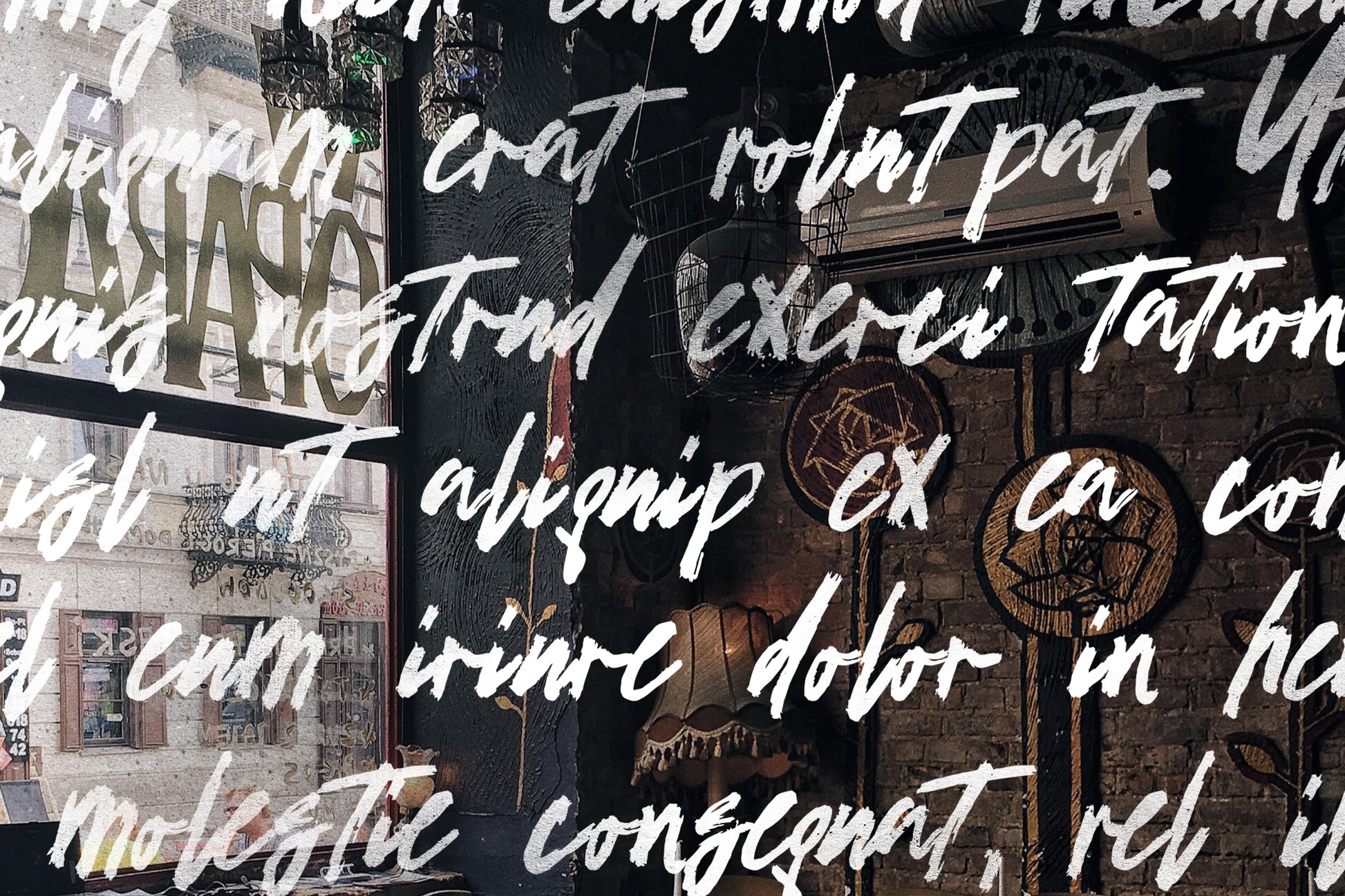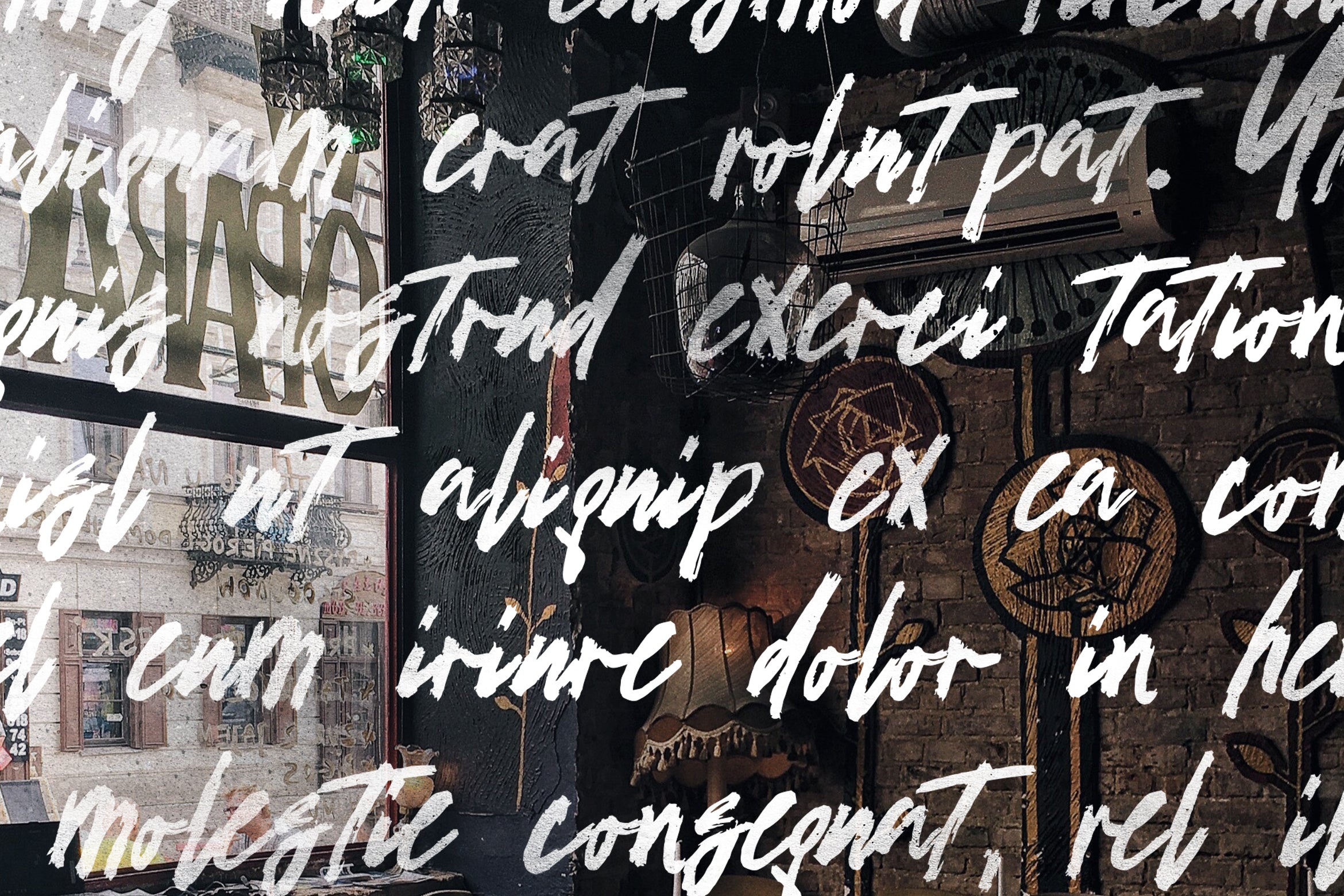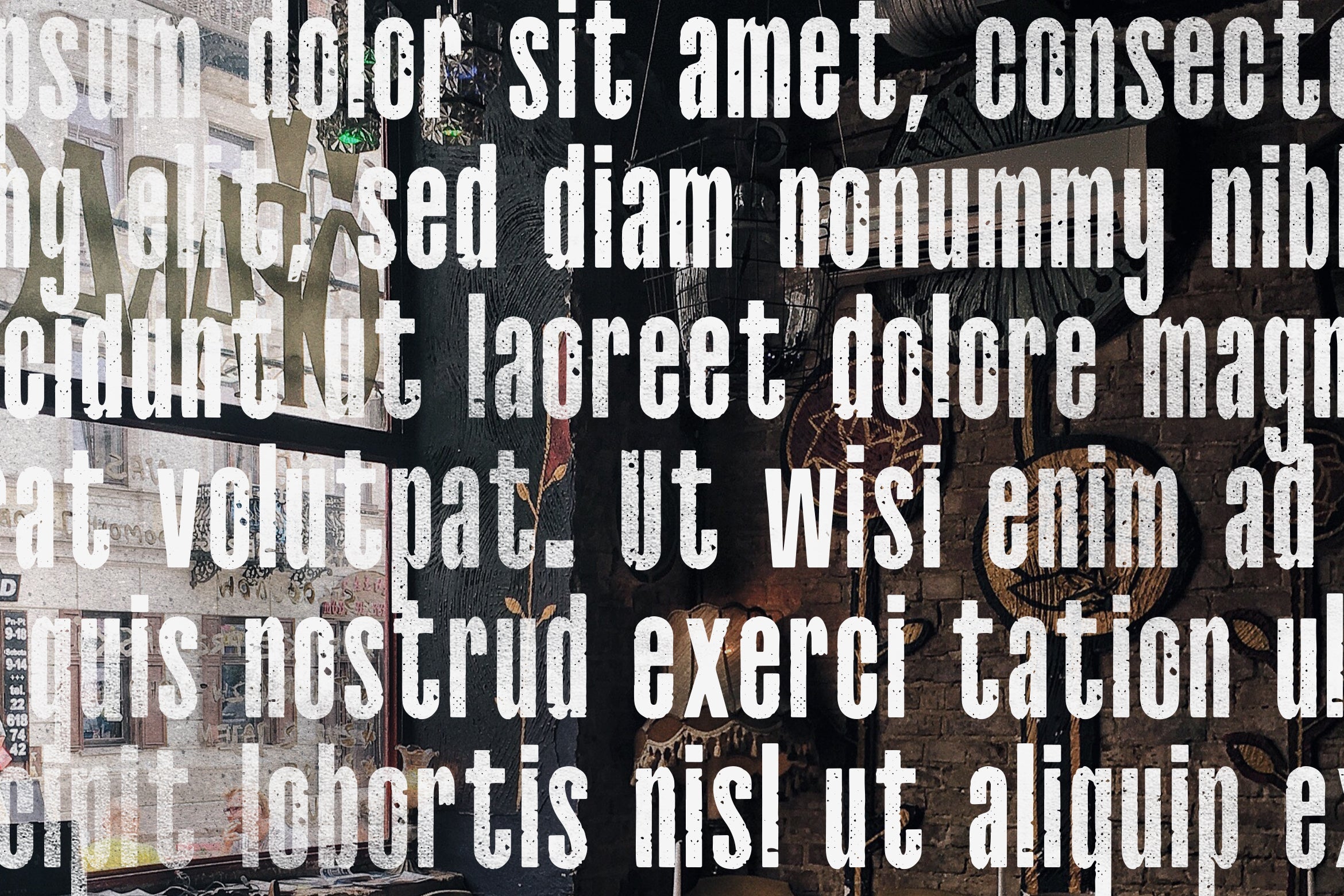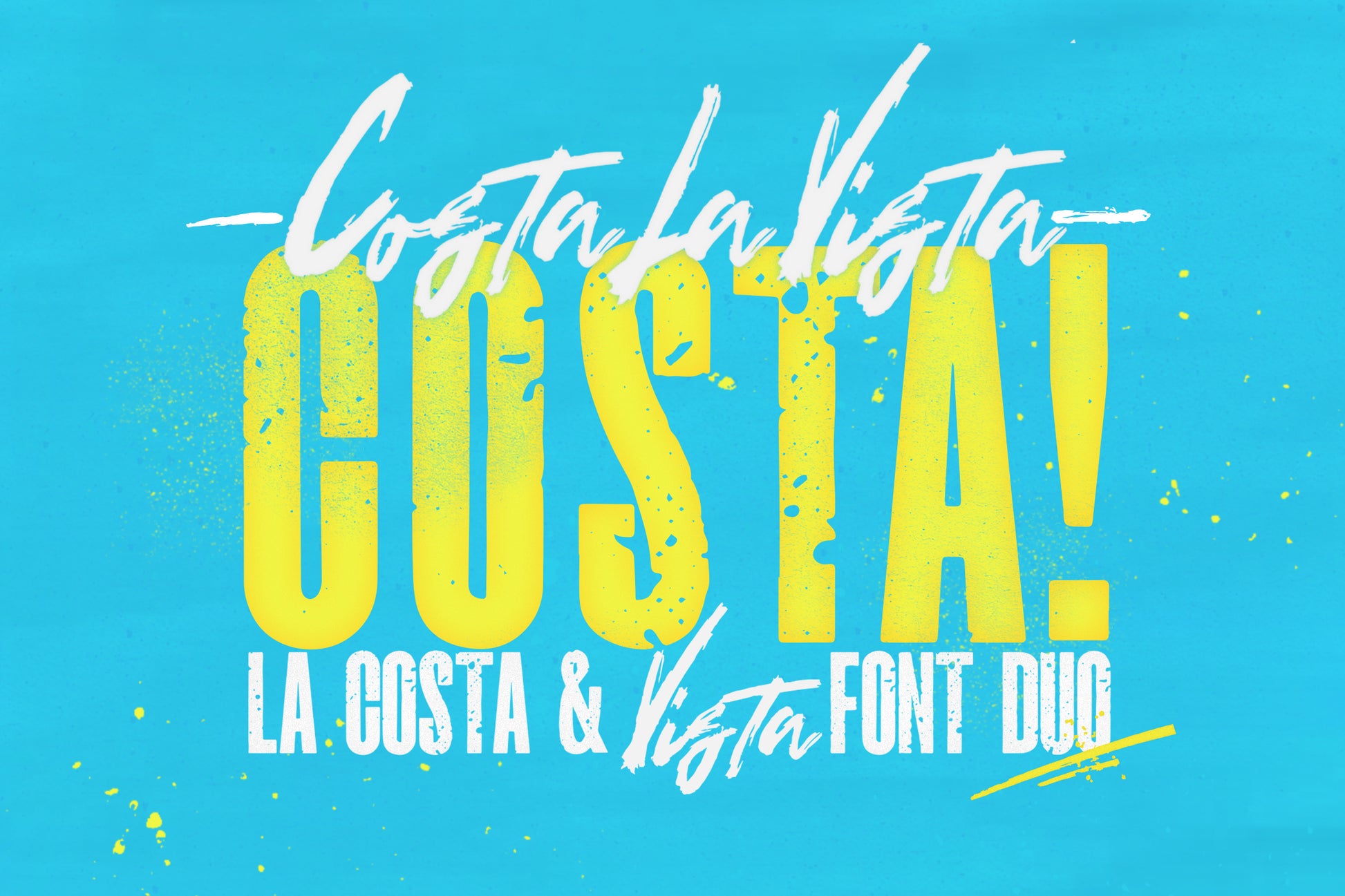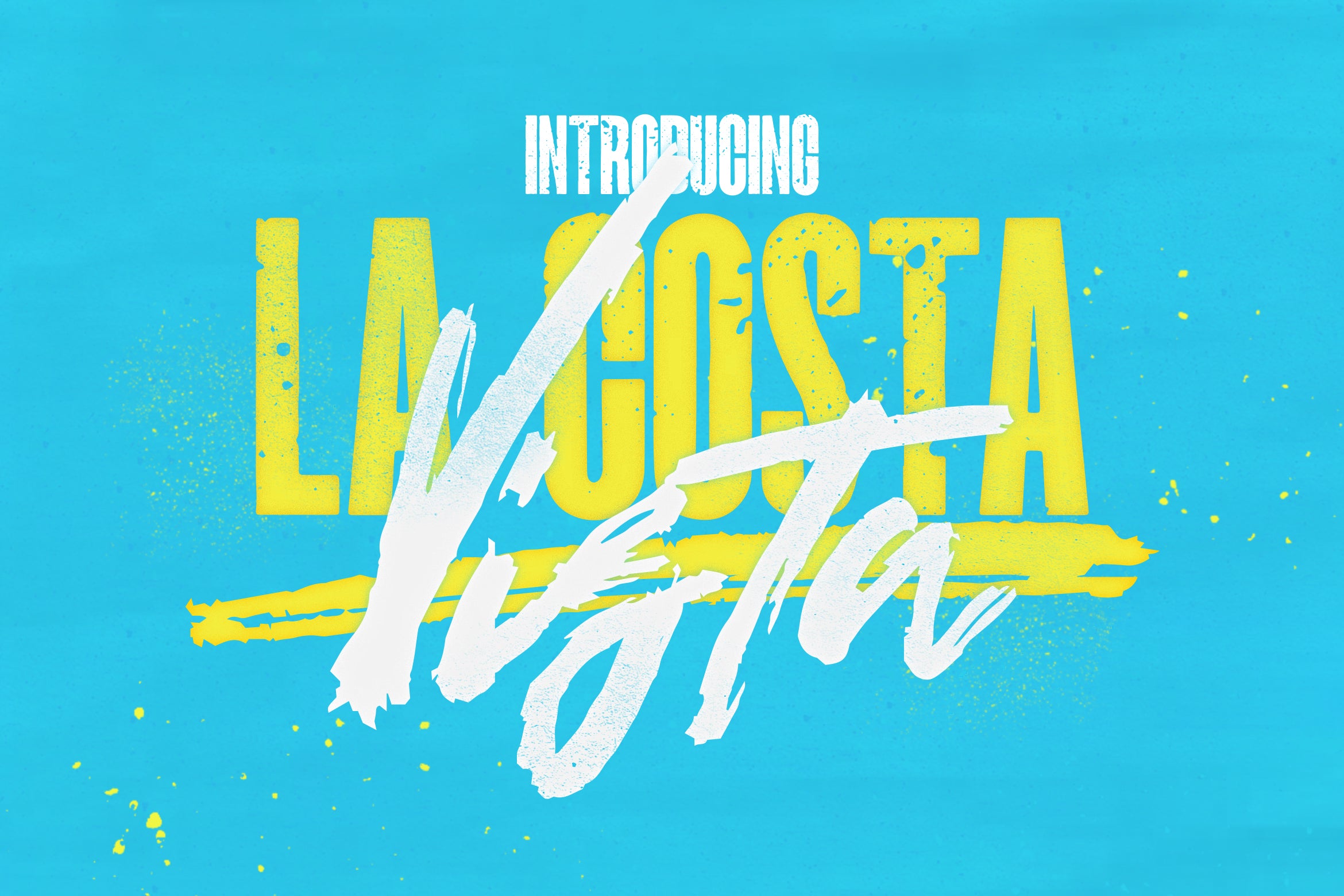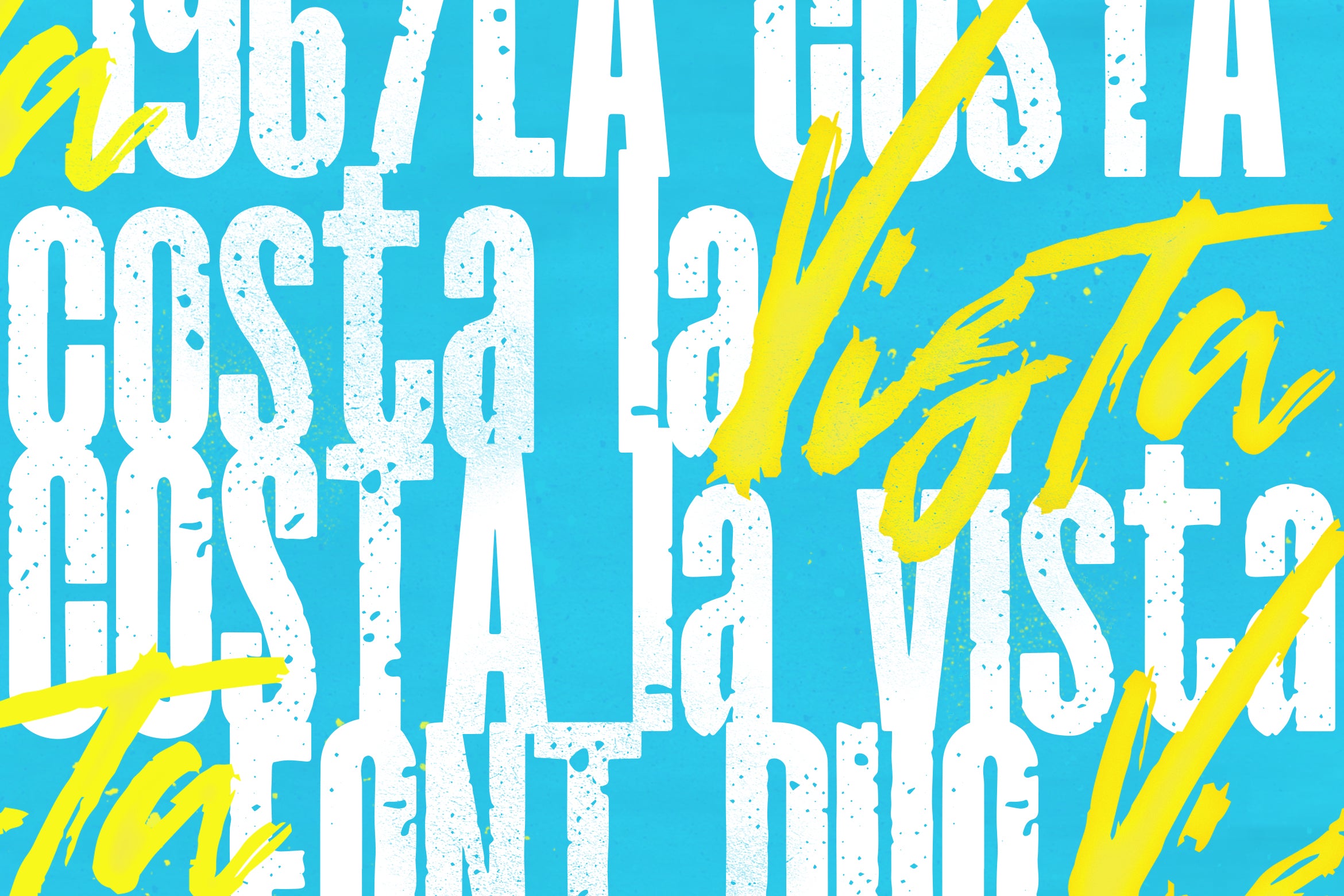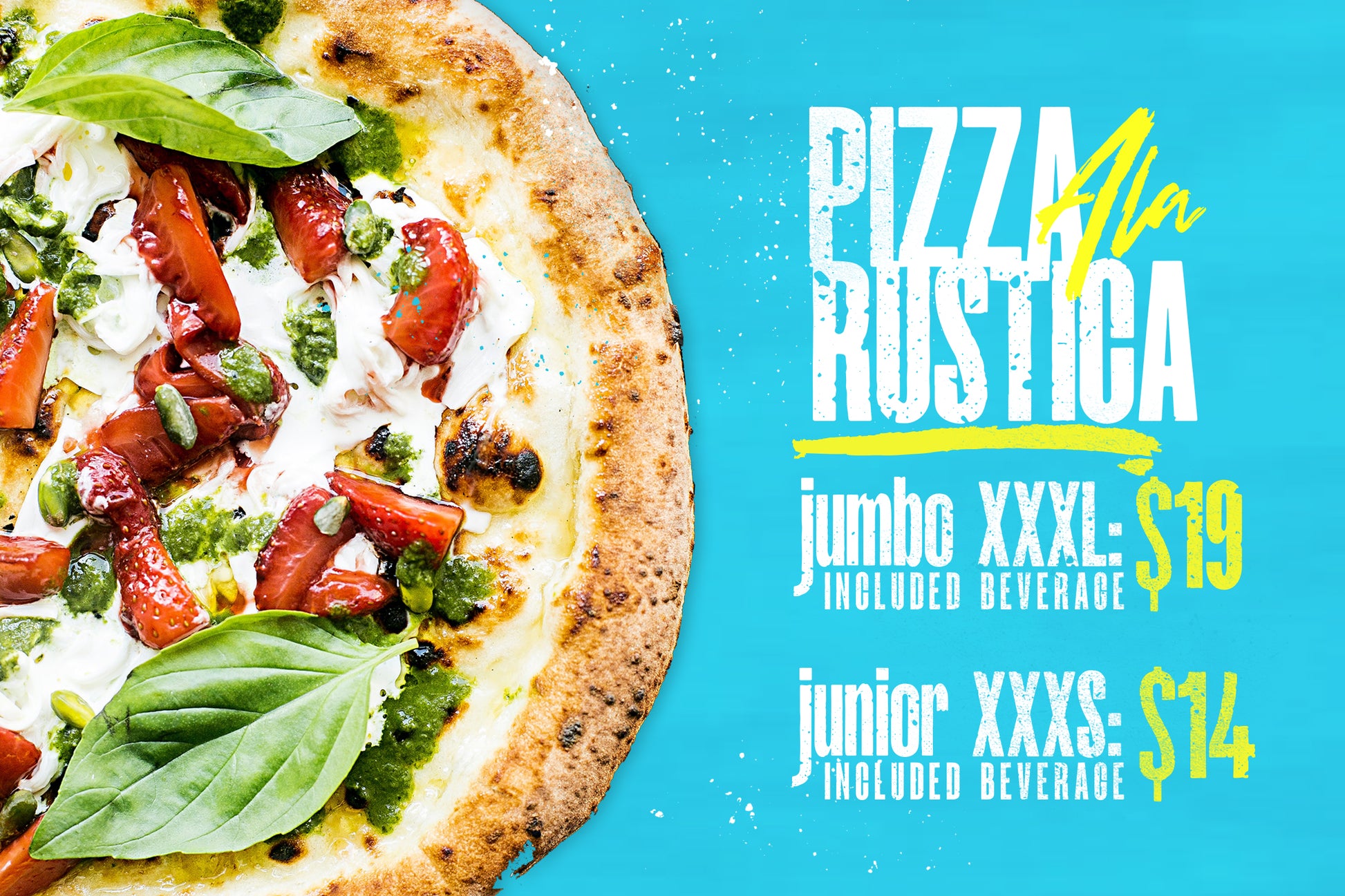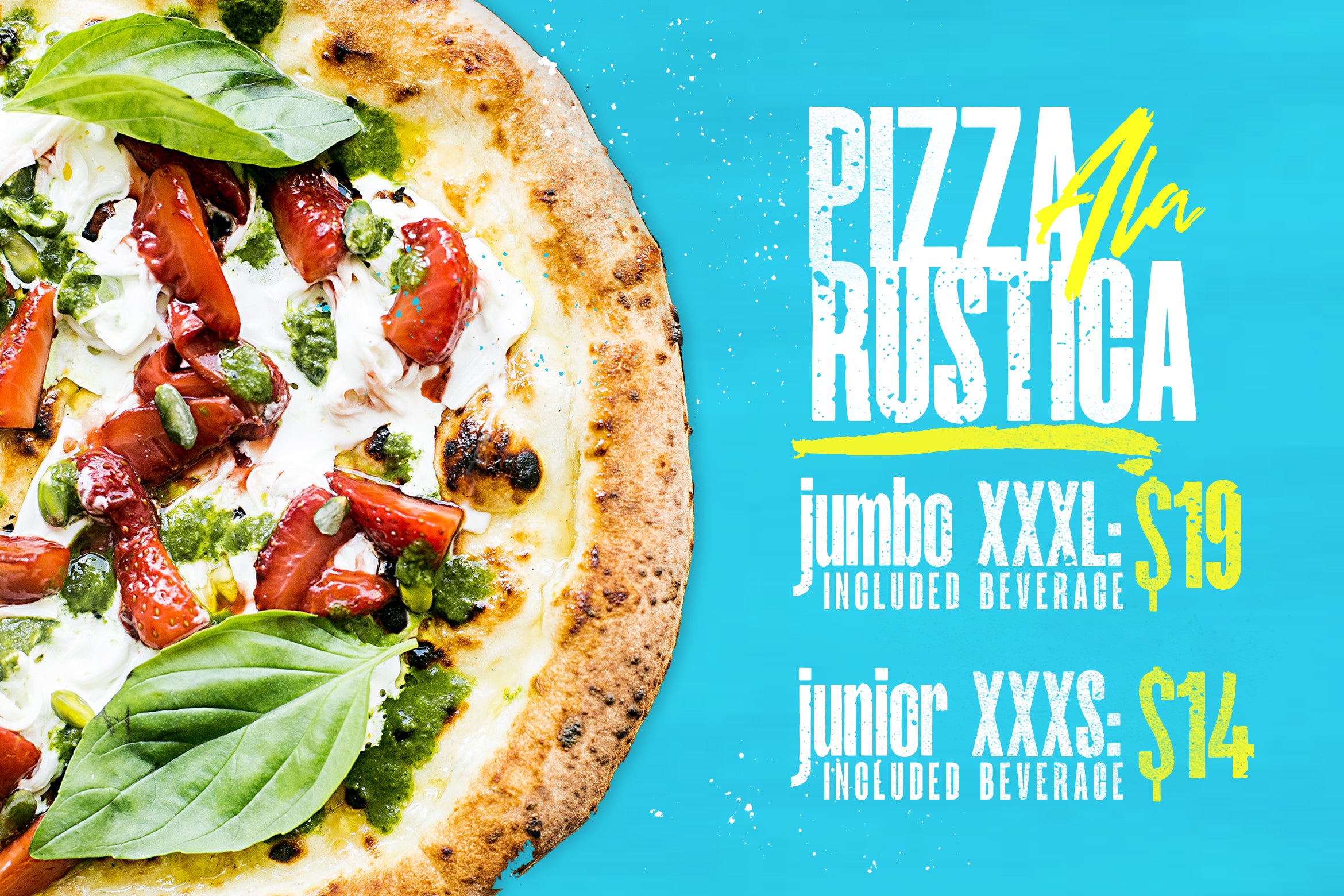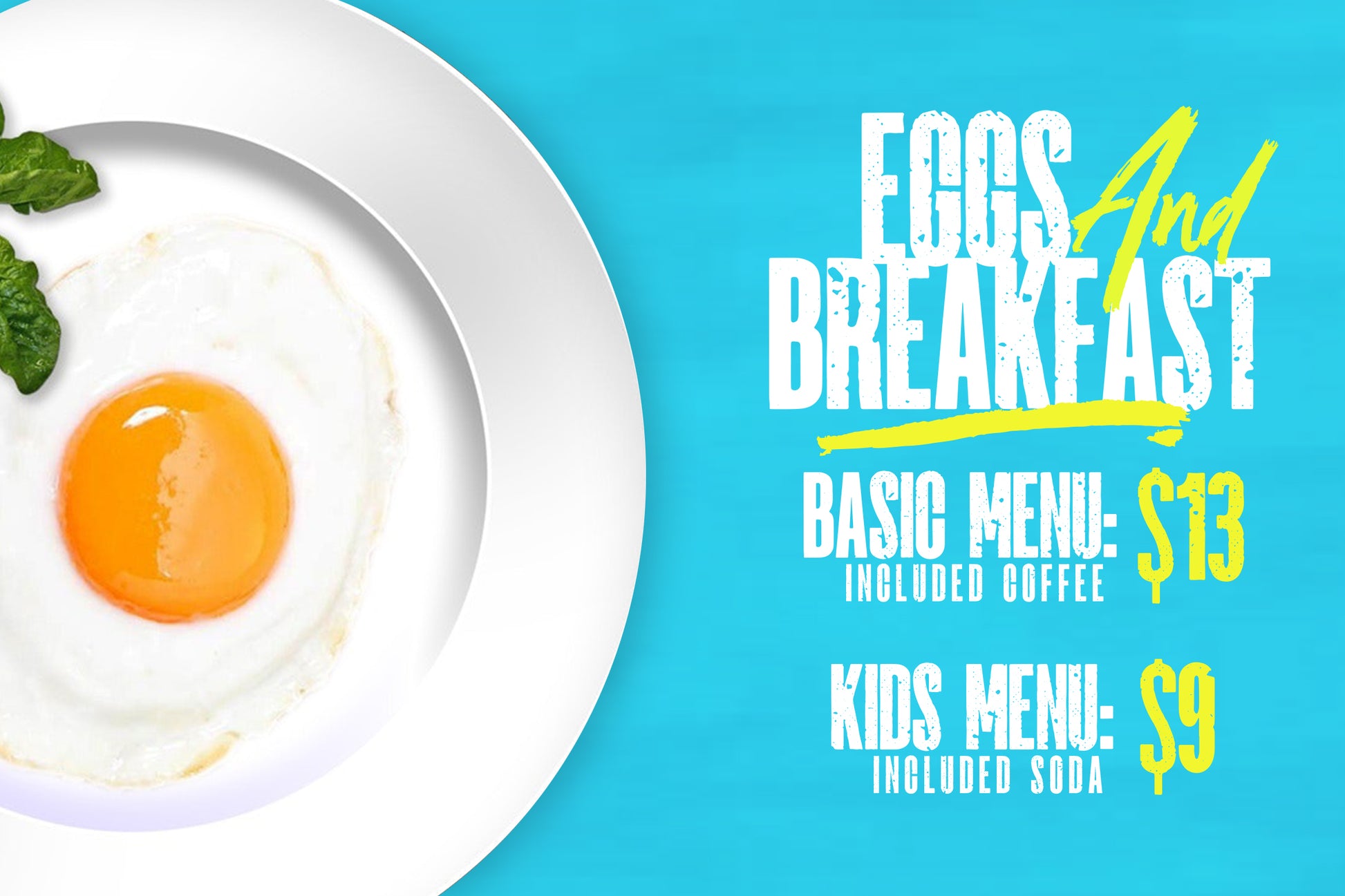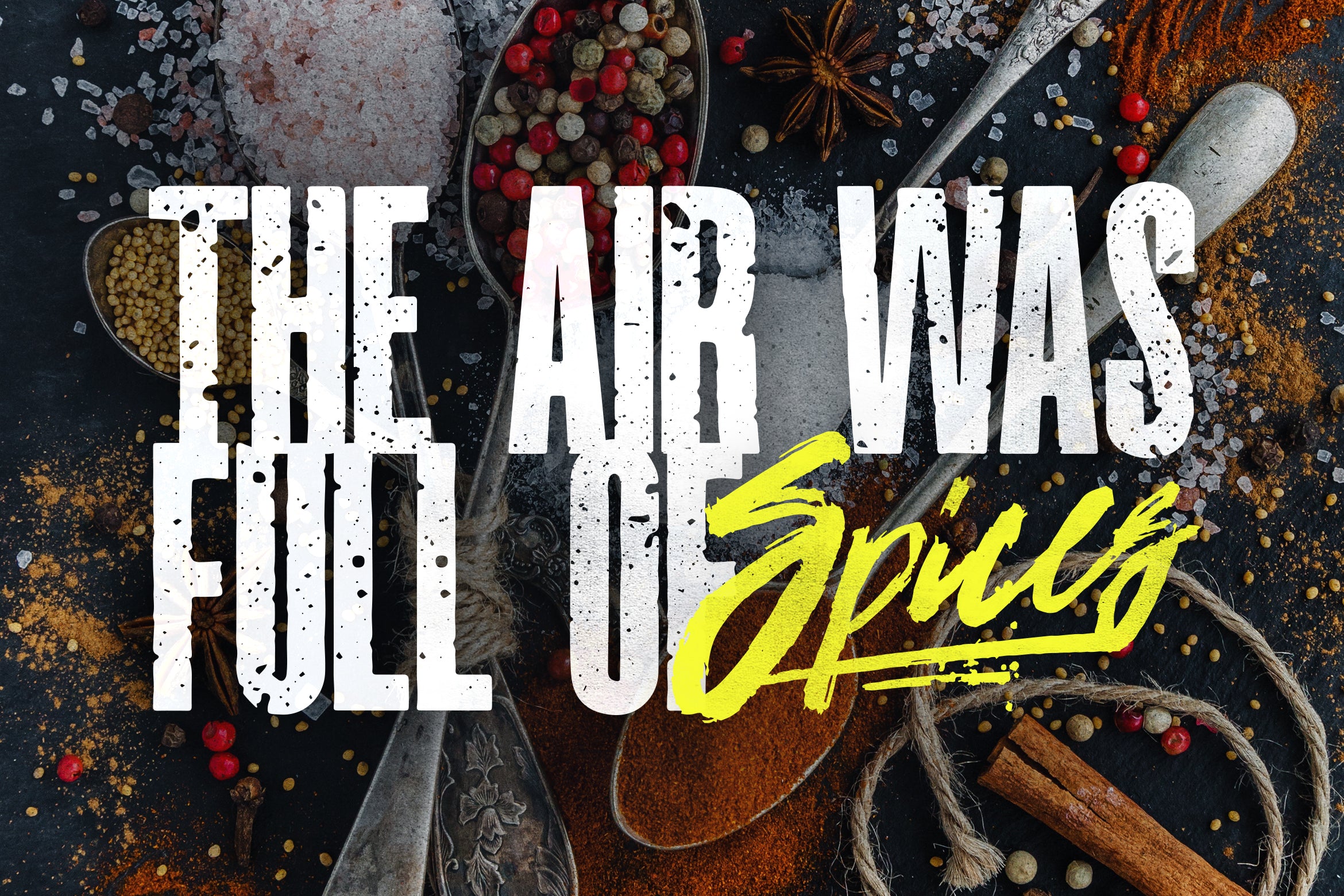
Fuente Costa La Vista
Costa La Vista Font es un dúo tipográfico (11 fuentes y estilos incluidos :-)) diseñado para titulares, títulos, pósteres, libros y prácticamente cualquier otra cosa. Posee un estilo único con formas condensadas y perfectas, inspirado en fuentes retro y texturizadas, y en tipografías geométricas impactantes que se quedan grabadas en la memoria. El conjunto también incluye fuentes cursivas para crear combinaciones innovadoras.
La fuente Costa La Vista es ideal para texto en pantalla, impresión y también para interfaces de usuario, dispositivos móviles, diseño web y carteles, con un conjunto de caracteres óptimos para su diseño en cualquier disposición.
Se ve especialmente bien en gran escala, aunque todavía lo lleva en tamaños de punto más pequeños.
Costa Book, Book Italic, Regular, Regular Italic, Bold.otf. Tipografía sans serif de inspiración retro con un toque moderno. Conjunto completo de mayúsculas y minúsculas, compatibilidad internacional y puntuación.
Vista.otf: Fuente manuscrita hecha a mano que incluye mayúsculas y minúsculas, con un conjunto completo de la A a la Z y compatibilidad con glifos estadounidenses y funciones básicas. Combina mayúsculas y minúsculas para crear estilos de texto interesantes.
Vista Italic.otf: Fuente MORE ITALIC hecha a mano que incluye todas las letras mayúsculas y minúsculas, con un conjunto completo de la A a la Z y compatibilidad con glifos estadounidenses y funciones básicas. Combina mayúsculas y minúsculas para obtener estilos de texto interesantes.
Vista Blur.otf: Fuente script difuminada hecha a mano que incluye mayúsculas y minúsculas, un conjunto completo de la A a la Z y compatibilidad con glifos estadounidenses y funciones básicas. Combina mayúsculas y minúsculas para crear estilos de texto interesantes.
La Costa .otf. Tipografía sans serif regular, retro, texturizada y con un toque moderno. Incluye mayúsculas y minúsculas, compatibilidad internacional y puntuación.
La Costa .otf ITALIC, tipografía sans serif retro texturizada con un toque moderno. Conjunto completo de mayúsculas y minúsculas, compatibilidad internacional y puntuación.
LaUnderlines.otf Subraya florituras y salpicaduras. Úsalos escribiendo cualquier letra de la A a la Z y combinándolas con letras normales.